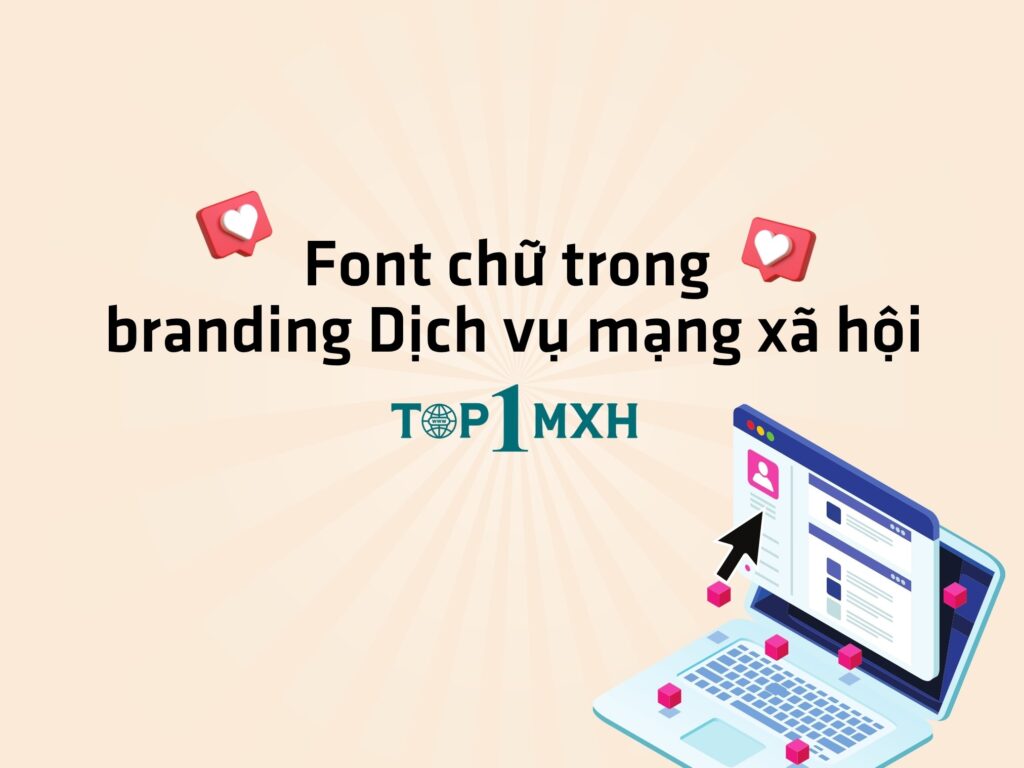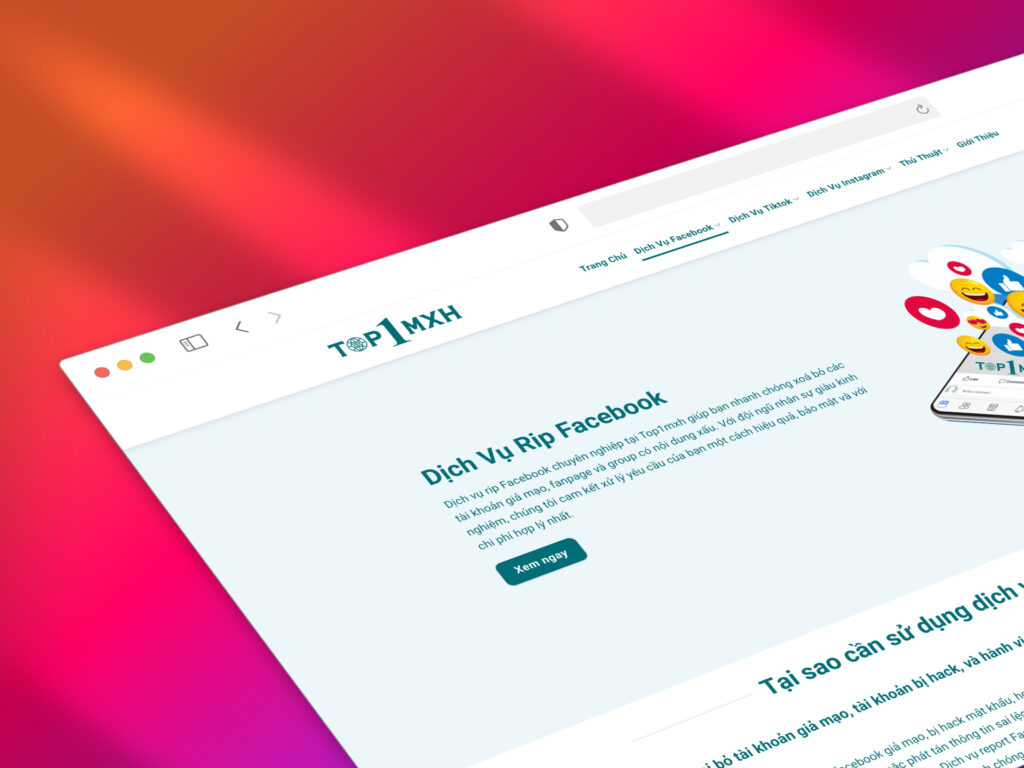
Top1MXH và hành trình xây hình ảnh chuyên nghiệp từ font chữ
Trong kỷ nguyên của mạng xã hội, hình ảnh thương hiệu không chỉ dừng lại ở logo hay màu sắc. Một yếu tố âm thầm nhưng có sức ảnh hưởng cực lớn đến cảm nhận của khách hàng chính là font chữ. Đặc biệt với các doanh nghiệp hoạt động trong lĩnh vực dịch vụ mạng xã hội như Top1MXH, việc lựa chọn và sử dụng font chữ phù hợp đóng vai trò then chốt trong việc thể hiện sự chuyên nghiệp, minh bạch và đáng tin cậy.
Font chữ trong branding Mạng xã hội: Nhỏ nhưng có võ
Trên Facebook, Instagram, TikTok hay Zalo, người dùng chỉ mất chưa tới 3 giây để quyết định có tiếp tục đọc một nội dung hay không. Trong khoảng thời gian cực ngắn đó, yếu tố thị giác là thứ đầu tiên tác động – bao gồm màu sắc, bố cục, hình ảnh, và đặc biệt là kiểu chữ.
Font không chỉ là công cụ để hiển thị văn bản, mà còn là “giọng nói thị giác” của thương hiệu. Một font hiện đại, rõ ràng sẽ giúp truyền tải sự chuyên nghiệp. Ngược lại, một kiểu chữ cũ kỹ, khó đọc hoặc lỗi dấu tiếng Việt sẽ làm giảm độ tin cậy ngay lập tức.
Những lỗi chọn font khiến dịch vụ MXH mất điểm
Nhiều đơn vị cung cấp dịch vụ mạng xã hội hiện nay vẫn mắc phải các sai lầm nghiêm trọng trong việc sử dụng font, điển hình như:
• Sử dụng font không hỗ trợ Unicode, gây lỗi dấu tiếng Việt
• Thiết kế bài post với font lòe loẹt, thiếu sự đồng nhất về style
• Dùng font không phù hợp với lĩnh vực dịch vụ (ví dụ: font hài hước cho nội dung nghiêm túc)
• Không đồng bộ font giữa các nền tảng: website – fanpage – tài liệu tư vấn
Hệ quả là khách hàng có thể cảm thấy thương hiệu thiếu đầu tư, thiếu chuyên nghiệp – dẫn tới tỷ lệ chuyển đổi thấp, giảm hiệu quả tiếp thị.
Top1MXH – Dịch vụ uy tín cần đi cùng hình ảnh chỉn chu
Top1MXH là đơn vị hàng đầu trong lĩnh vực xử lý tài khoản giả mạo, dịch vụ Rip Facebook, bảo vệ thương hiệu cá nhân và hỗ trợ kỹ thuật MXH tại Việt Nam. Với đặc thù hoạt động liên quan đến dữ liệu, bảo mật, tính pháp lý và phản ứng nhanh trên môi trường số, Top1MXH cần một hình ảnh thương hiệu rõ ràng, mạnh mẽ, và đồng nhất.
Đó là lý do vì sao font chữ trở thành một phần quan trọng trong bộ nhận diện của họ. Không chỉ dùng cho bài đăng trên social media, Top1MXH còn cần font chữ phù hợp để áp dụng trong các tài liệu gửi khách, ảnh minh họa hướng dẫn, form liên hệ hoặc báo cáo dịch vụ.
Gợi ý combo font Việt hóa dành riêng cho Top1MXH:
• UTM Avo Bold: font tiêu đề rõ ràng, dứt khoát, thể hiện sự quyết liệt và đáng tin trong xử lý vấn đề MXH
• Be Vietnam Pro: font body tối ưu hiển thị, thân thiện với người dùng mobile, chuẩn SEO, hỗ trợ đầy đủ tiếng Việt
• iCiel Lemon Milk: sử dụng cho các đoạn nhấn mạnh (CTA), tạo điểm nhấn hiện đại nhưng không quá “lòe loẹt”
Font Be Vietnam Pro
Với bộ font đúng, bạn không chỉ “đẹp” hơn – bạn còn trở nên dễ tin hơn, dễ đọc hơn, chuyên nghiệp hơn trong mắt khách hàng – yếu tố sống còn với các dịch vụ hoạt động trong không gian mạng.
Xây thương hiệu online, đừng để font làm bạn tụt lại
Top1MXH là minh chứng cho thấy, dù hoạt động trong ngành “nóng” như rip Facebook, thì việc xây dựng hình ảnh thương hiệu chỉn chu vẫn rất cần thiết. Và font chữ – tuy nhỏ – lại đóng vai trò cực kỳ lớn trong toàn bộ quá trình đó.
Nếu bạn đang làm trong ngành social media, đã đến lúc xem lại: “Font bạn đang dùng có đang nói đúng tiếng nói thương hiệu bạn muốn truyền tải không?”